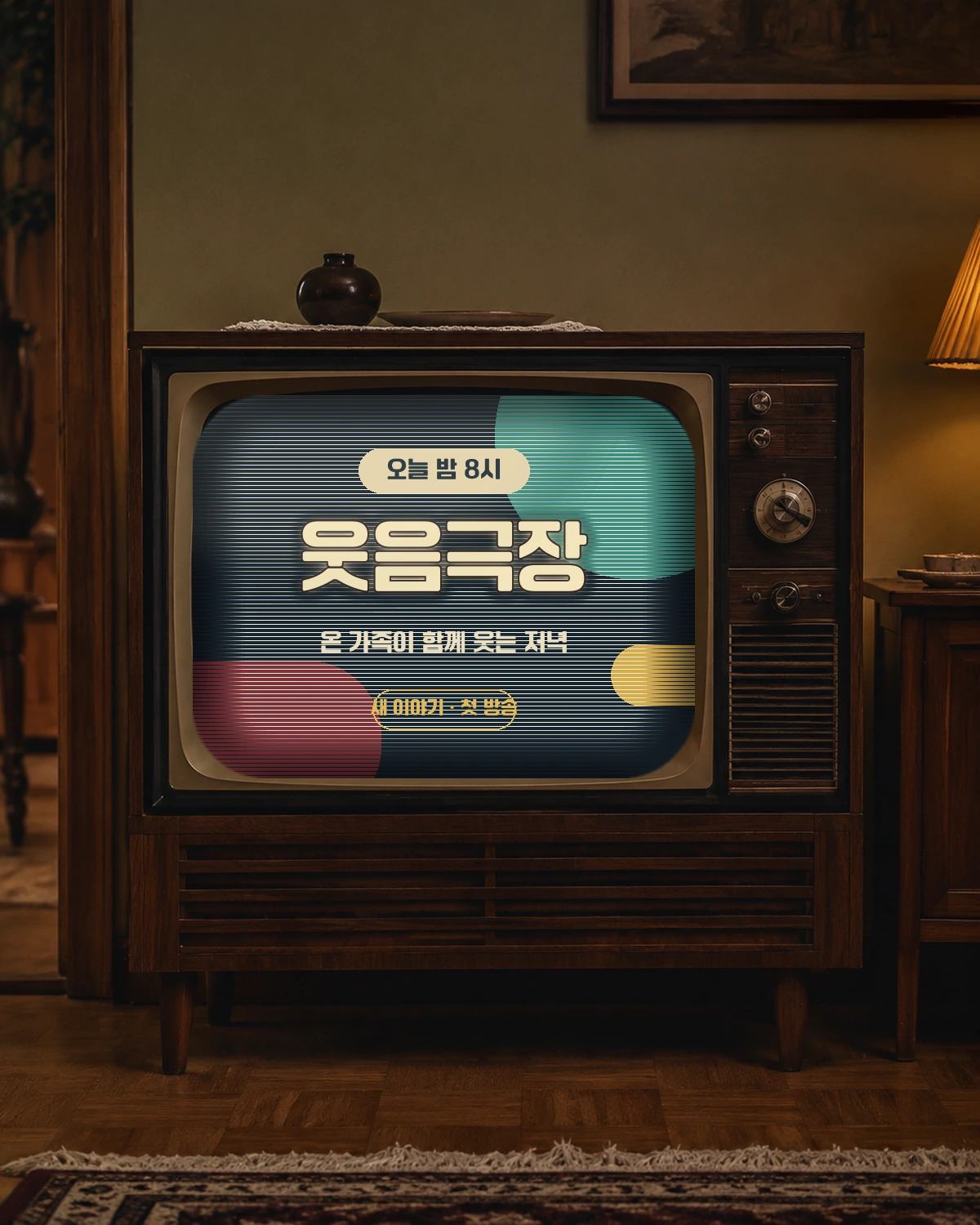
MBC1961 굴림 — (주)문화방송에서 배포하는 무료 폰트입니다. 1961년 인사동 사옥의 옛 간판, 그 모듈 형태를 현대적으로 되살린 레트로 제목용 굴림체
문화방송이 창사 60주년을 맞아 2021년 첫날부터 무료로 푼 서체입니다. 모티브가 구체적입니다. 제작사 설명 그대로 1961년 MBC 인사동 사옥의 옛 간판을 모티브로, 1960년대 모듈 형태의 간판 느낌을 현대적으로 재해석한 제목용 폰트입니다. 이름의 1961은 개국 연도입니다.
이 계열은 두 종으로 나뉘는데 성격이 다릅니다. 굴림이 붙지 않은 MBC 1961이 신뢰받는 공영방송의 채널 정체성을 담았다면, 이 굴림 쪽은 국민에게 사랑받는 친근하고 레트로한 느낌을 맡습니다. 획 끝을 둥글게 굴린 것이 그 차이를 만듭니다.